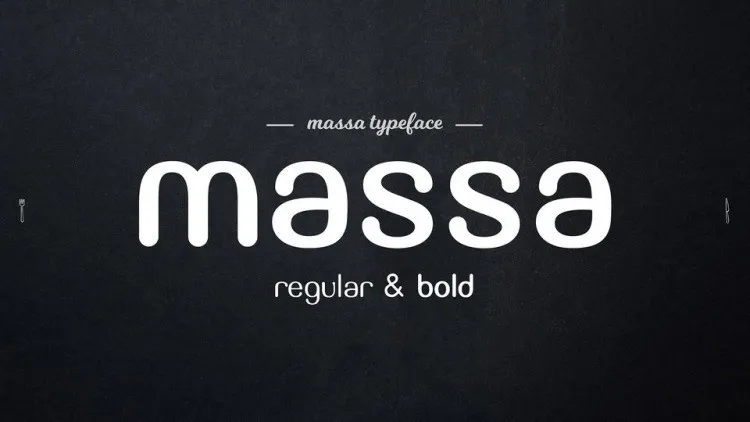
Massa Free Font – Download Grátis
Massa é uma tipografia sans serif clássica projetada para headlines, grandes textos, marcações, logotipos e usos expositivos. Esta tipografia também se destaca quando se trata de criar ótimas marcas, conteúdo promocional e gráficos publicitários que elevam os aspectos criativos do design. Se você está procurando uma fonte para sua próxima campanha visual ou projeto editorial, Massa é o tipo certo. Seu formato clean e moderno pode trazer uma dose de sofisticação aos seus projetos sem desvirtuar a essência e o propósito da informação que deseja transmitir. As amostras de exemplo acima ilustram a variedade de como ela pode se adaptar para diferentes usos, desde letrinhas grandes em banners até textos mais detalhados. Experimente Massa nas suas próximas criações gráficas e veja o que ela tem a oferecer. Se você está buscando uma fonte clássica com um toque de modernidade, não perca tempo. Massa está esperando por você.